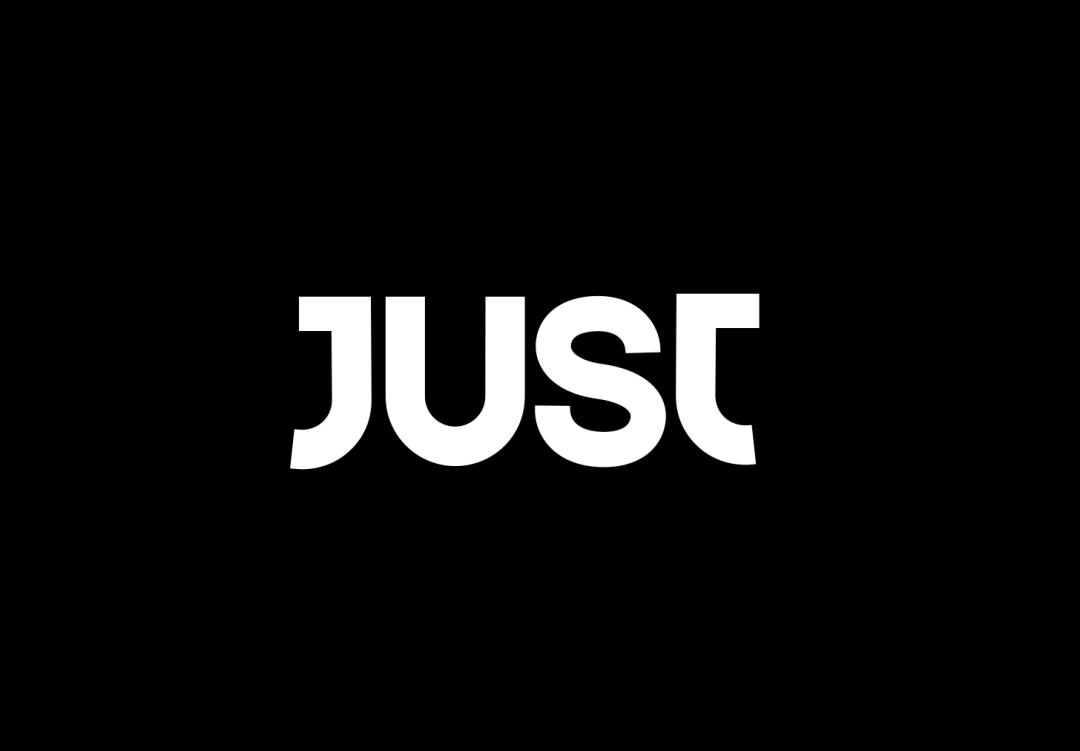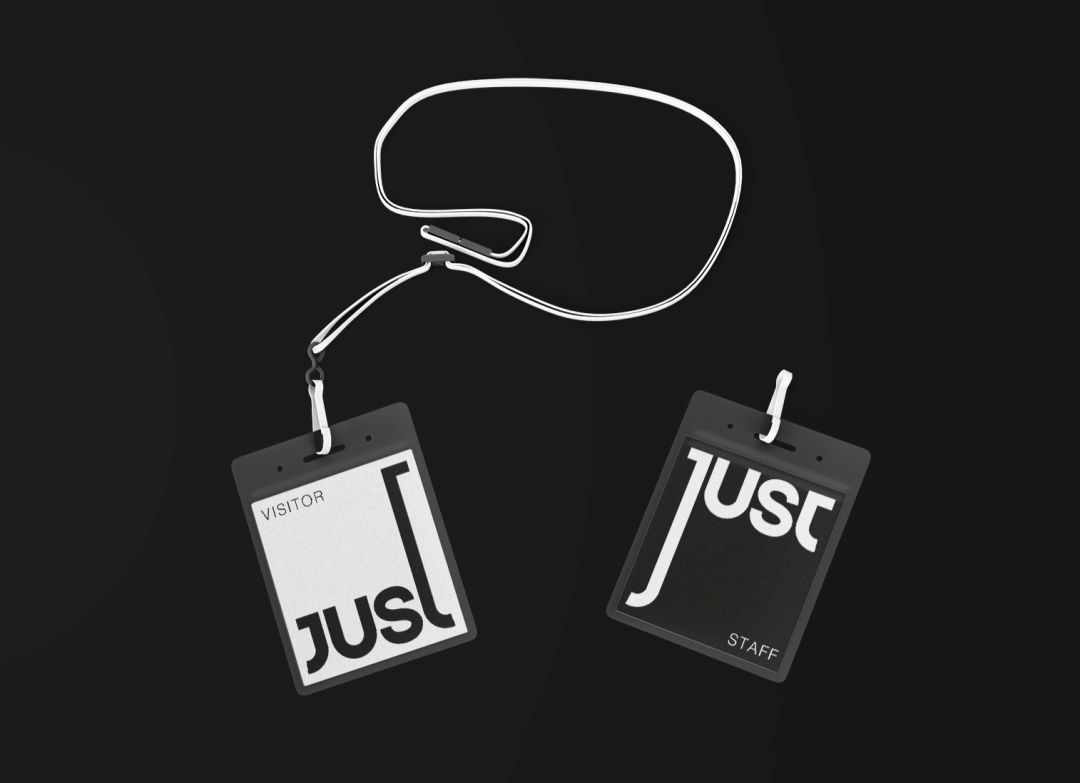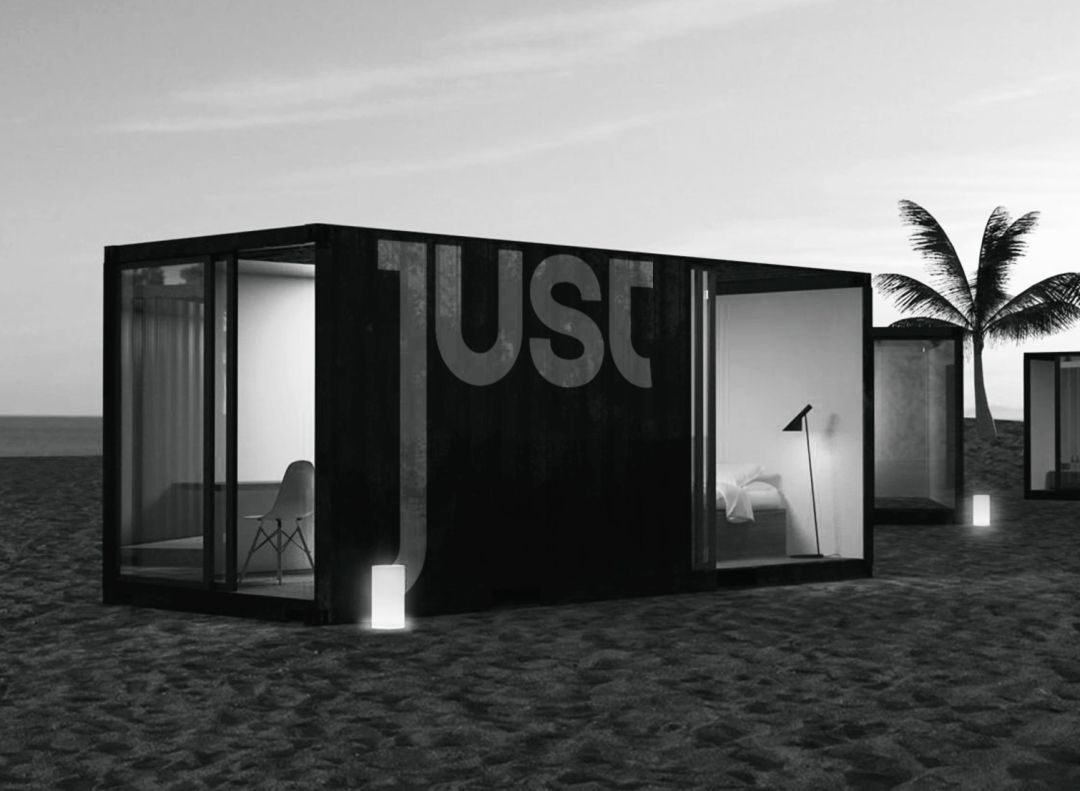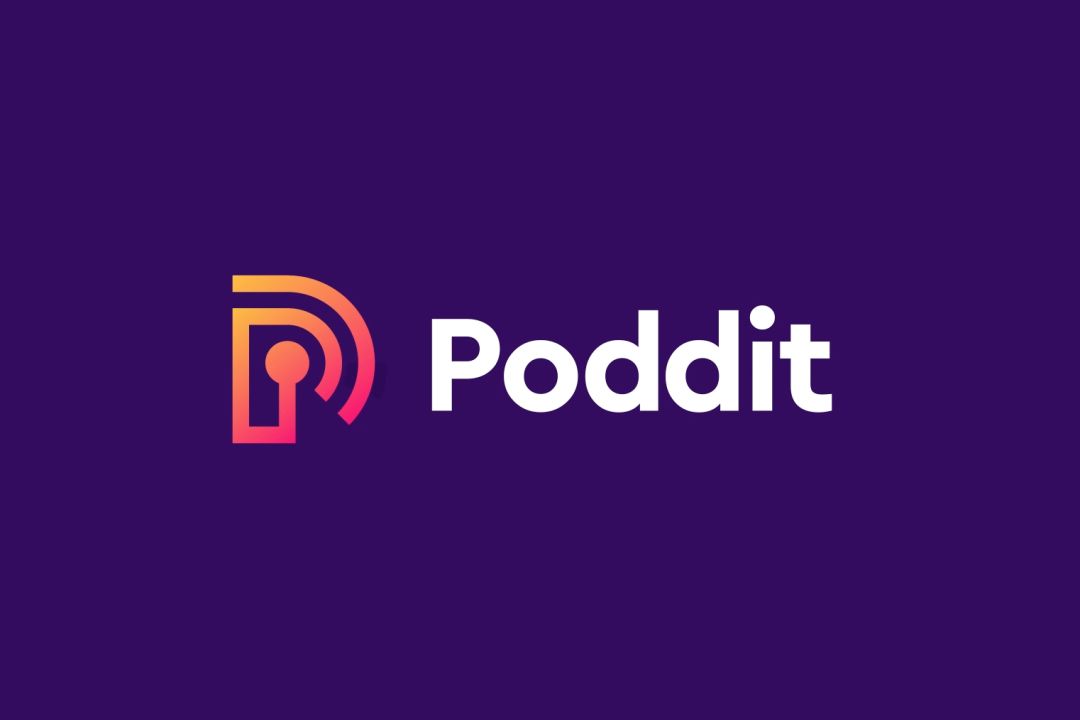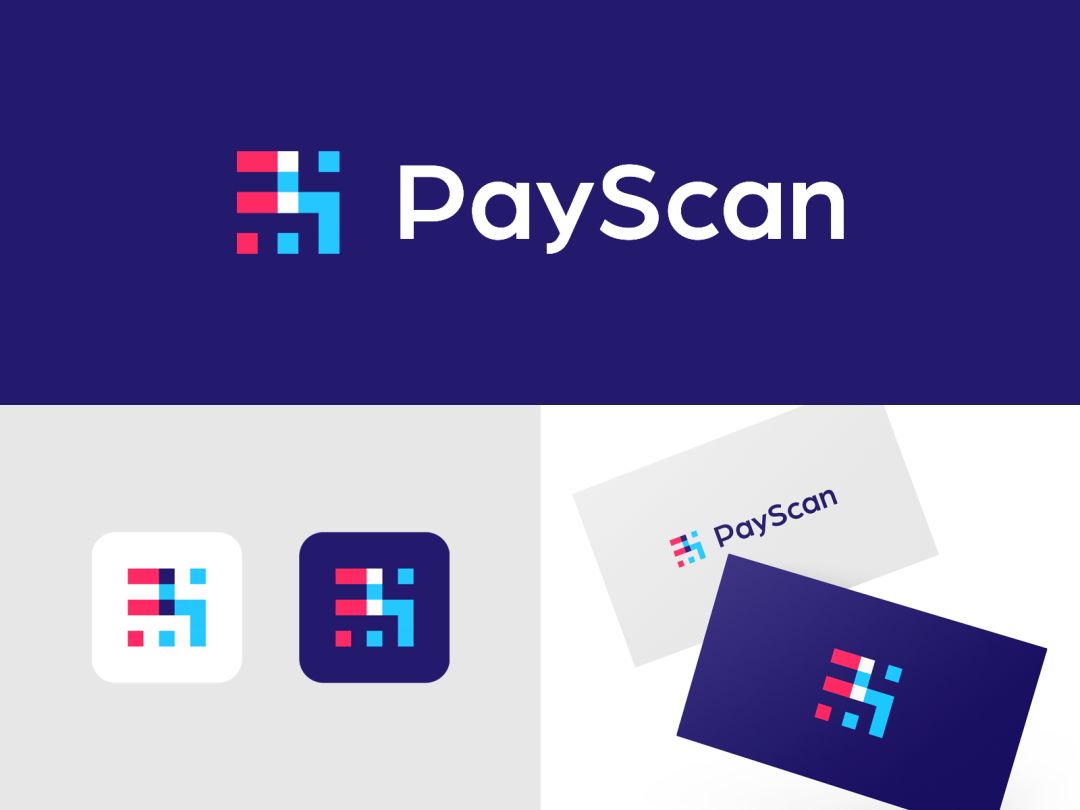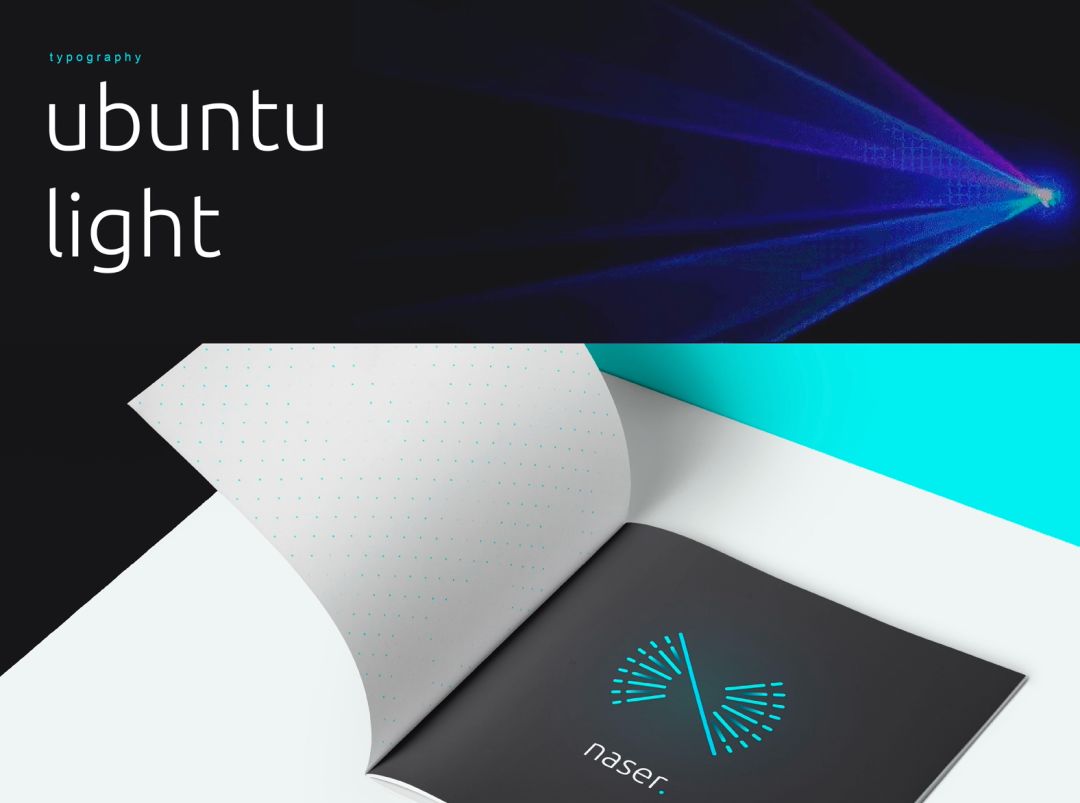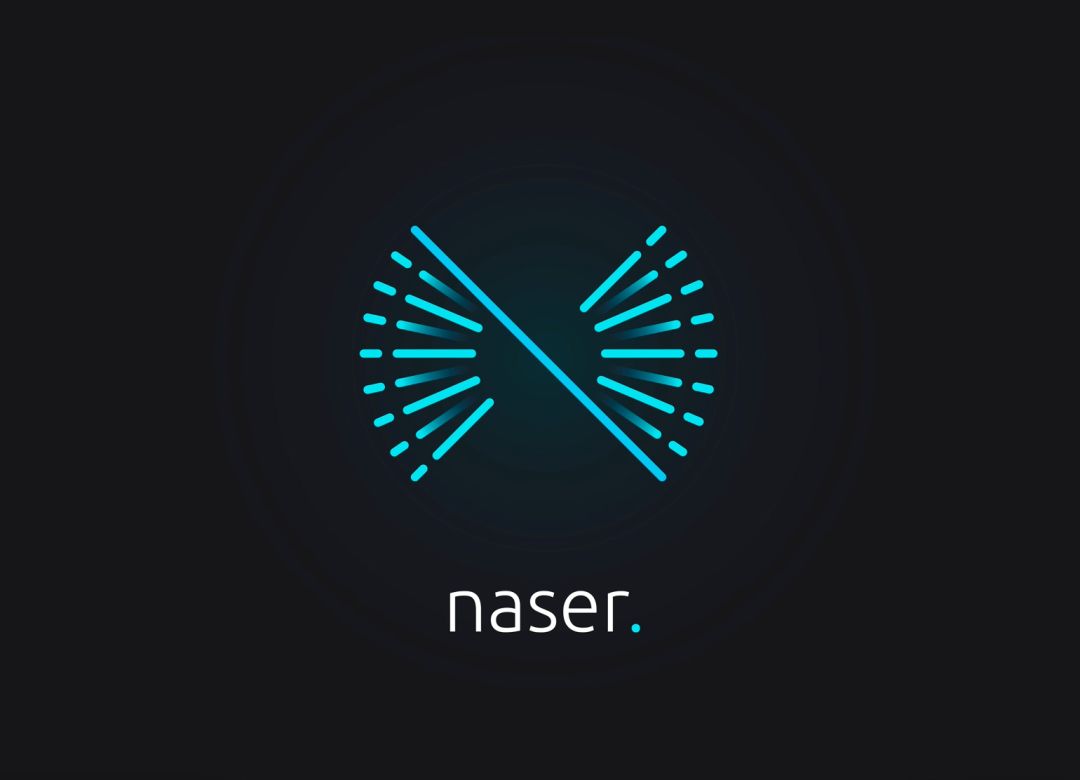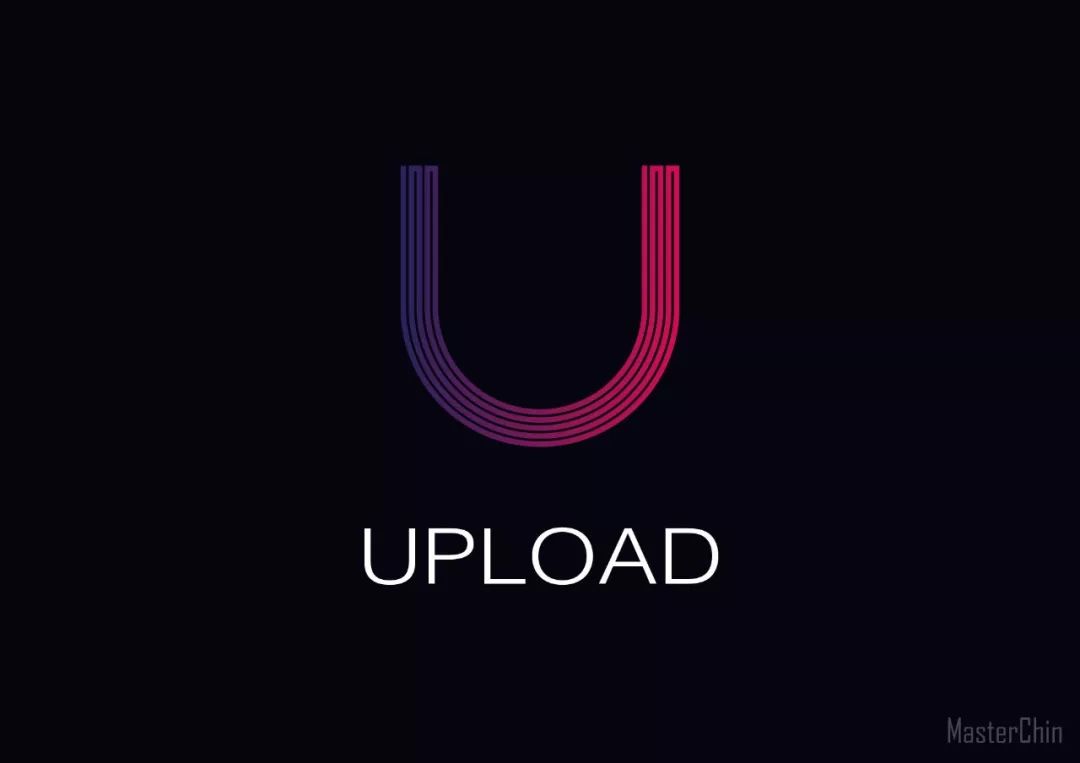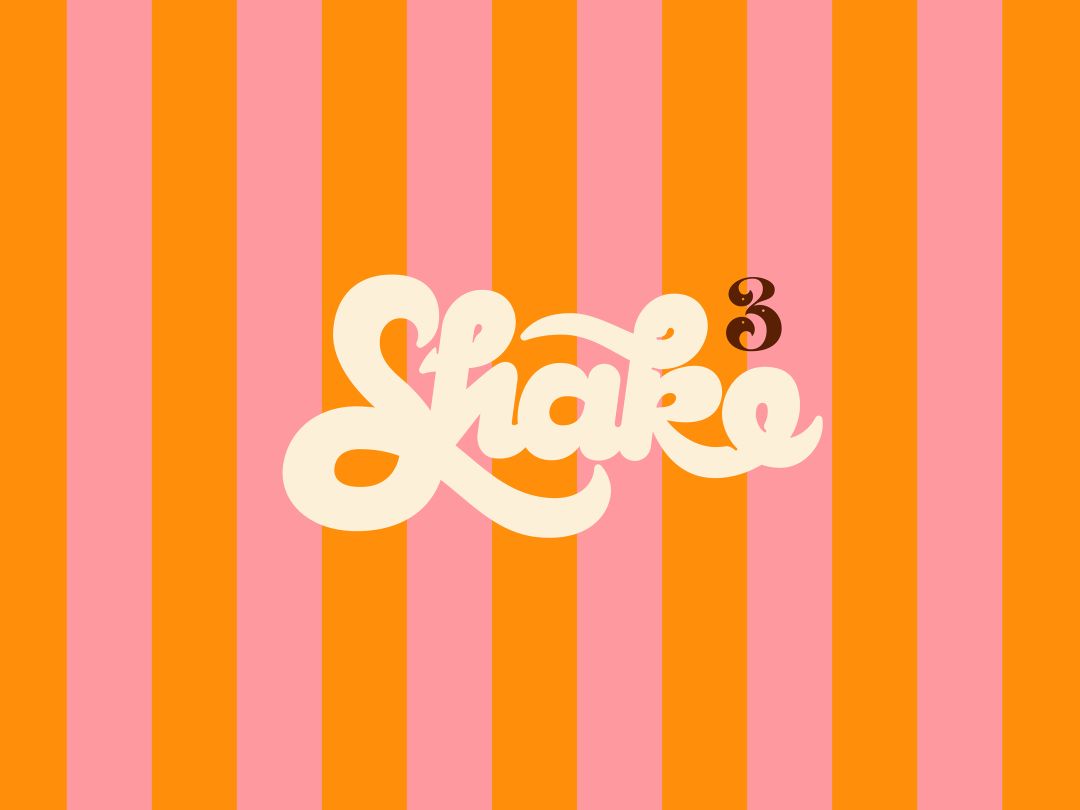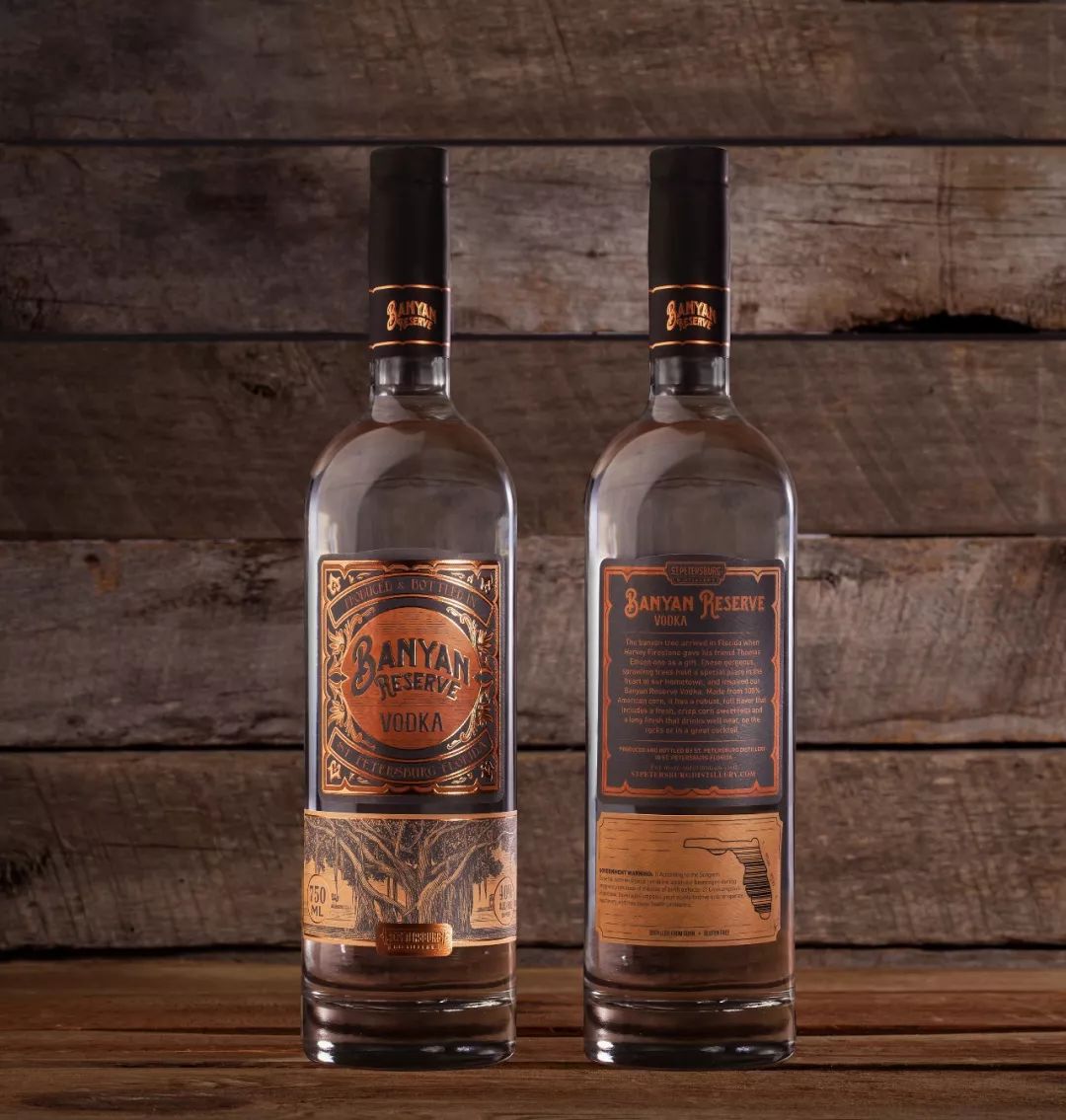
2020年LOGO设计趋势惊艳登场。LOGO设计是平面设计中非常重要的领域,虽然受平面设计大趋势的影响,但LOGO设计趋势通常比较稳定,每年不会有很大的变化。因为一个LOGO的使用寿命是很长的,直到公司想要优化之前。尽管如此,设计师也要设计出时髦别致的LOGO。今天我们来预测一下2020年LOGO设计领域最流行的趋势吧!
有趣的LOGO=友好的品牌
卡通LOGO与趣味、积极乐观以及愉悦的心情相关联。那些想要被消费者欣然接受的品牌,通常会选择卡通LOGO,并基本能凭借第一印象就赢得潜在客户的心智。在2020年将要大火的不仅是卡通LOGO,还有动画化的卡通LOGO。动画化增添了图案的趣味性,更消除了品牌与消费者之间的隔阂。原因很简单,因为它们看起来友好、亲切。用类似马克笔的粗线条勾勒出LOGO轮廓,是公认的2020年LOGO设计趋势之一。这些图案简约而趣味十足,它们不一定很精细,但是放大缩小看起来却很棒。design by:Nikita Melnikov提及插图类的LOGO,则是大道至简,而扁平风无疑是最简约的LOGO风格。无论是添加一些细节,还是全部简化为扁平化,这都是为了让LOGO更加生动活泼。
最近在平面设计中大肆流行的涂鸦风也渗透到LOGO设计趋势上了。涂鸦就类似于铅笔或马克笔的素描、手绘等。转换到LOGO设计上,意思就是简单随性的手作图案。design by:Elmira Gokoryan
黑白LOGO永不过时,它们优雅、简约、不喧宾夺主。而且黑白在配色上显得很安全,也不容易出差错。黑白能给人一种高级神秘、沉稳大方的感觉。
所见即所得,一目了然
无论是为了描述品牌核心价值,还是品牌核心业务,LOGO通常都会自带一些或深或浅的隐藏含义。设计师绞尽脑汁,希望能让好LOGO“自己会说话”,同时还能保持简约。目前很流行的方法是正负形技巧与部分字母置换手法。
线条、矩形、波点、曲线
由基础几何形状构成的极简LOGO将继续引领潮流,极简主义LOGO设计是设计界的风格风向标。它们易于细致地应用在品牌识别材料中而不被混淆,为了进一步提升识别度,设计师们常常使用专用色值,以及与黑白版本成套的配色方案。
矩形象征着平衡与稳定,品牌方往往喜欢用它来传达品牌信息。矩形可能在2020年的LOGO设计中愈发显著,只不过不会以正形直接呈现。design by:Bruce Mau Design
是极简主义的完美范例,它们可以看作是各种基本形状的复合元素。在2020年的LOGO设计中,线性LOGO传达着自由、开放、简约与活力。这些线条无论是为了形成一个具体的形状还是承载一个隐含的信息,设计师都将持续发挥线性创造力,设计出惊艳的极简主义LOGO。
是非笔直的线条,它们充满活力与创造力,设计师可以创造出任何形状。在未来的一年,我们将看到平行曲线、混沌式曲线、装饰曲线与嵌入式曲线融入在LOGO设计作品当中。
作为基础的几何形状之一,圆形自带深厚的文化含义,以圆形为基础的LOGO具有完整、完美、无限的含义。此外,在字体LOGO设计中,设计师通常将圆形与粗壮的字体相结合,达到更强有力的气场。
专治单一色彩
接下来的一年中,LOGO中的渐变设计将会继续流行。渐变设计可以将将简单的图形摇身变成实打实的色彩矩阵,相近颜色之间的无缝过渡使LOGO更具动态,也更迷人。
渐变LOGO设计中最新的流行技法之一,将明亮而生动的色彩有机融合成绚烂的调色板。基于不同的设计需求,调色板可以展现出创意主题中未来主义的梦幻视觉。
为了让LOGO更简约或更符合品牌色的调性,设计师会选择更单元或单一的色彩,这并不意味着他们不能使用多色渐变色来增添设计的动感。而运用近似渐变,能让你的LOGO更和谐,同时不失品牌识别性。design by:Jeroen van Eerden
复古风潮不仅仅是LOGO设计趋势,更是2020年整个平面设计趋势的潮流。无论是使用古旧纸张、邋遢的特效,还是复古的图案或配色方案(即质朴柔和的色调),复古设计是一个宏观的回溯大潮,是凌驾于时髦的时尚。
在LOGO设计中运用金银等金属质感元素,意味着华丽与高级。在2020年,金属质感风潮会是LOGO字体与标志界的当红一炮。金属质感与LOGO(如名片、铭牌、广告物料等)结合后,格调感立马提升几个档次。
为特定LOGO定制专属字体,一直是企业与独立设计师的最爱。LOGO字体设计在LOGO设计中的分量可想而知,它们既可以从字面上表达含义,也可以赋予更多设计感。
等距LOGO与模拟3D LOGO将在2020年享有一席之地。在2D平面上描绘3D物体,这种LOGO风格好就好在创造了一种视觉深度。与渐变、轮廓描边、明亮色等其他潮流设计相结合,咱们将会在未来一年见识到大量的等距视图风格LOGO作品。
使用时尚的半透明设计元素这一势头估计在明年依然不减。LOGO中的半透明设计看起来很酷的同时也不失重要的承载力,品牌可用它来表达有助于塑造品牌信誉。